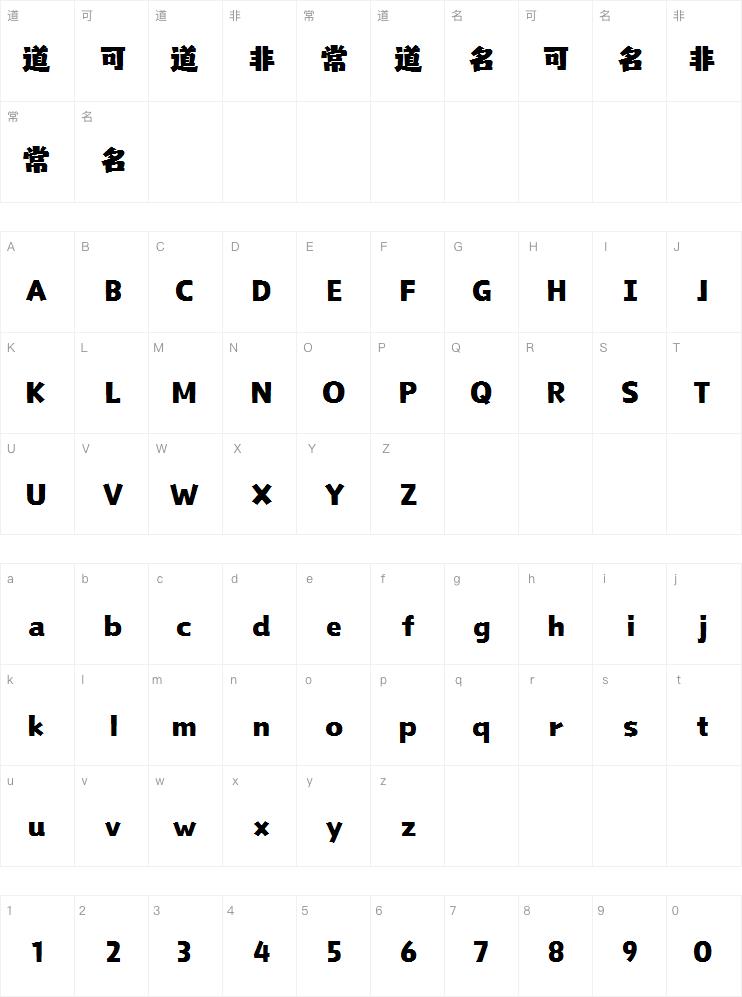
山海趣黑w
山海趣黑,是一款全新的字体,包含汉字9169个,符号200+个。该字体是一款综艺标题黑体字体,是一款具有强劲视觉冲击力的综艺风格标题字体。字形充实填满整个字框,造型硬朗,直线的笔画构成坚实有力,简洁明了的笔画切角;笔画有连笔设计,直线与弧线交相呼应,使得字形带有律动感,带来强有力的视觉冲击效果。该字体在综艺体的基础上做了诸多创新,使得该字体既有着流动的美感,又有着端肃的凝重,在正式用字场合落落大方,在日常使用环境中不失亲切友好,能够在保留综艺体基本特征的基础上更能适应当下时尚潮流的需要,助力各大新产品夺取标题主战场。